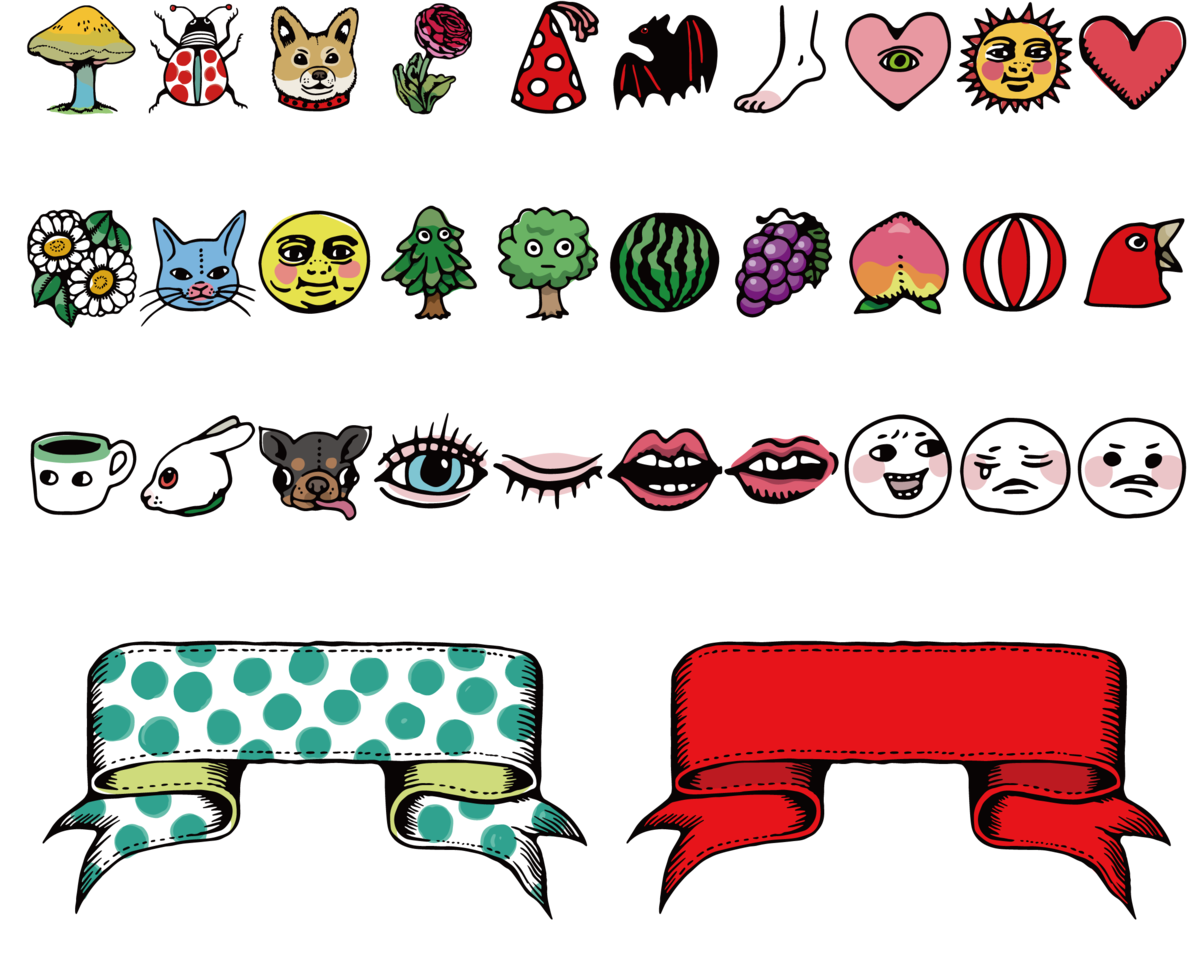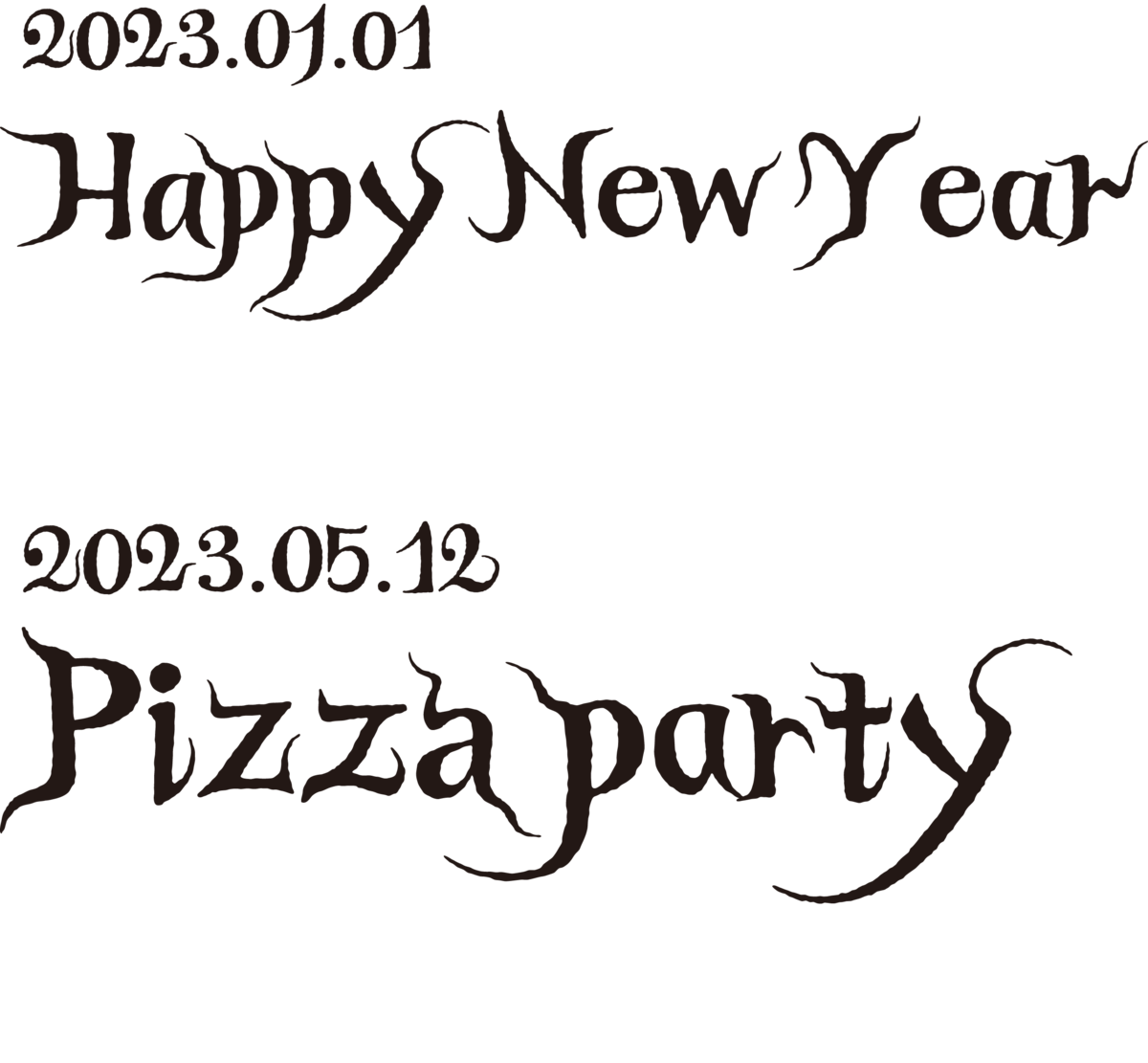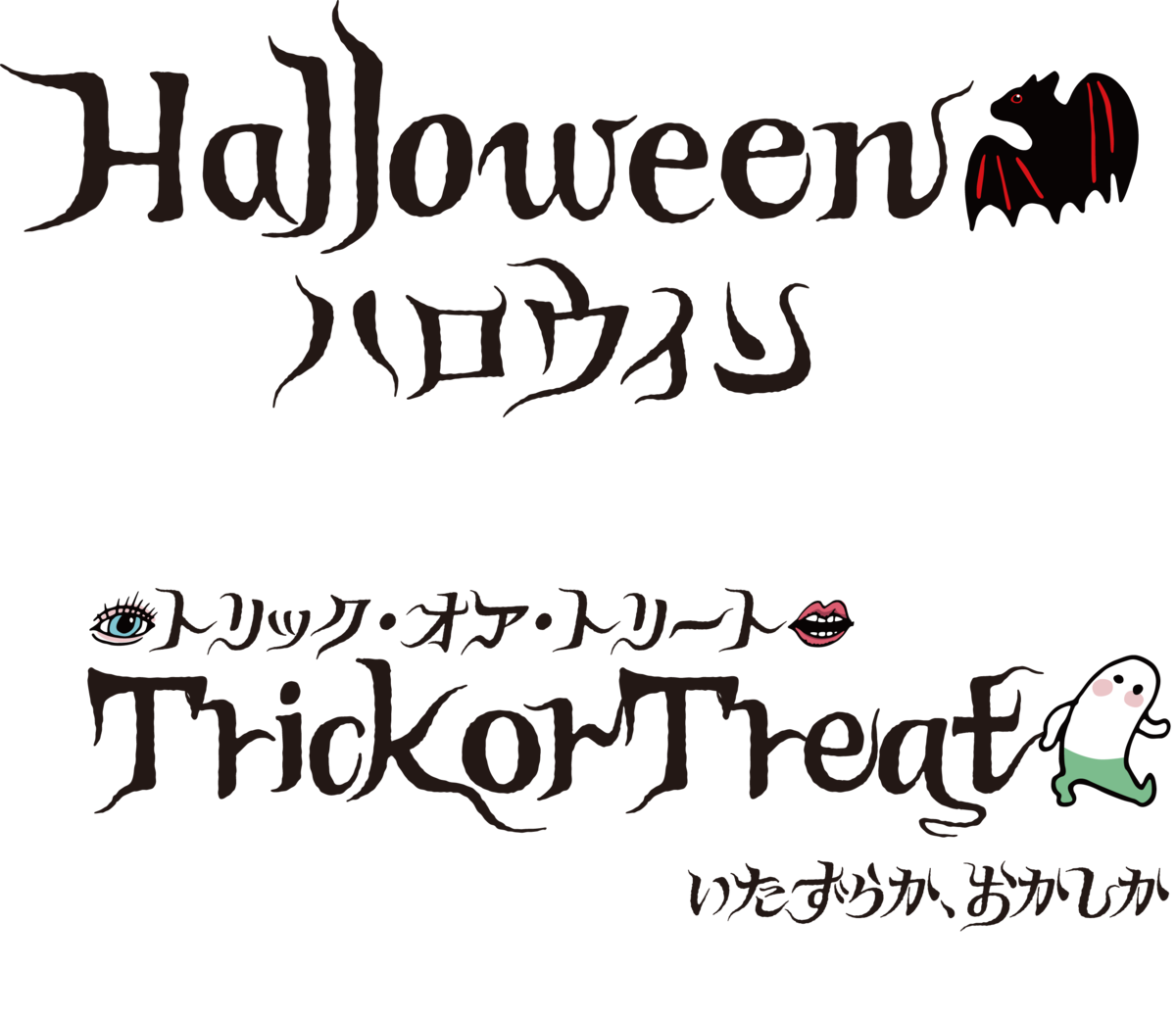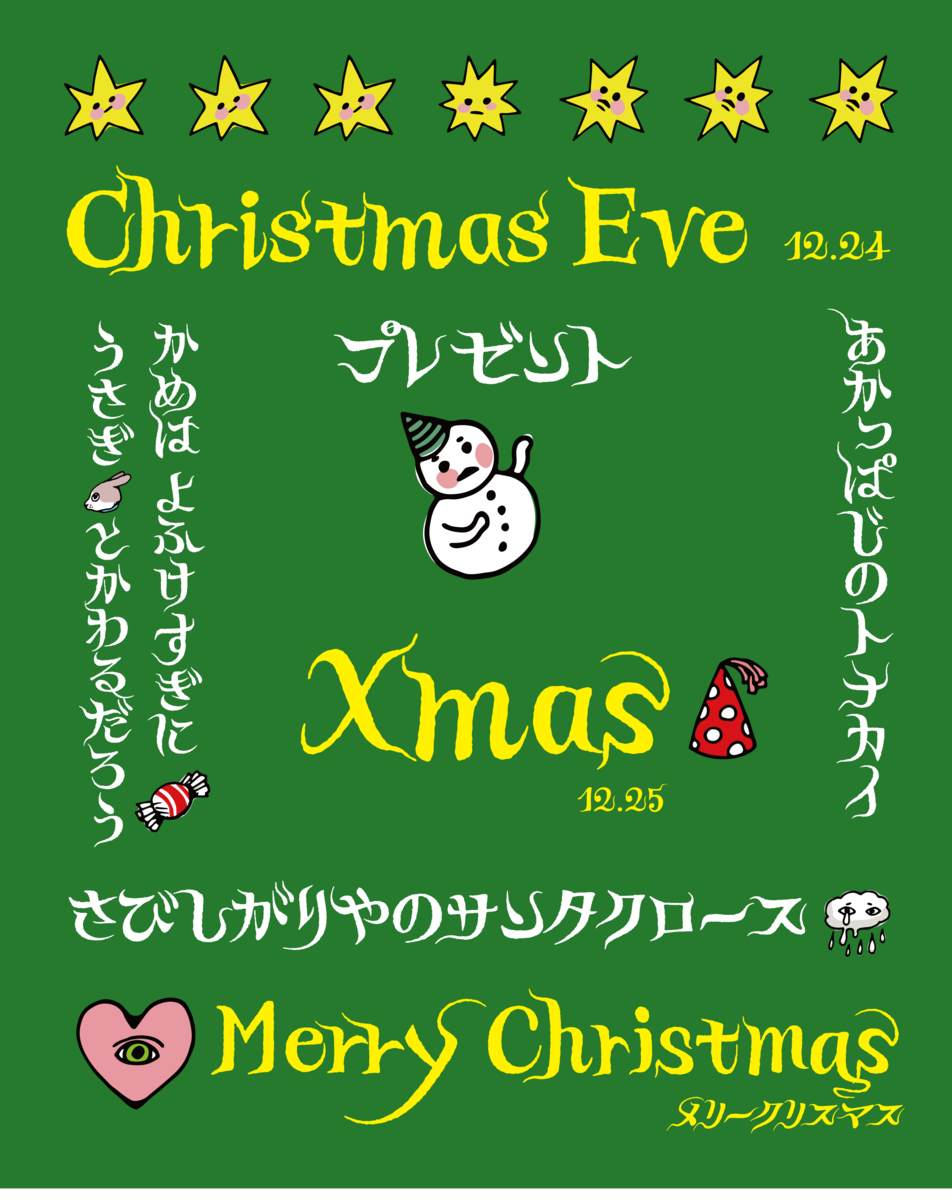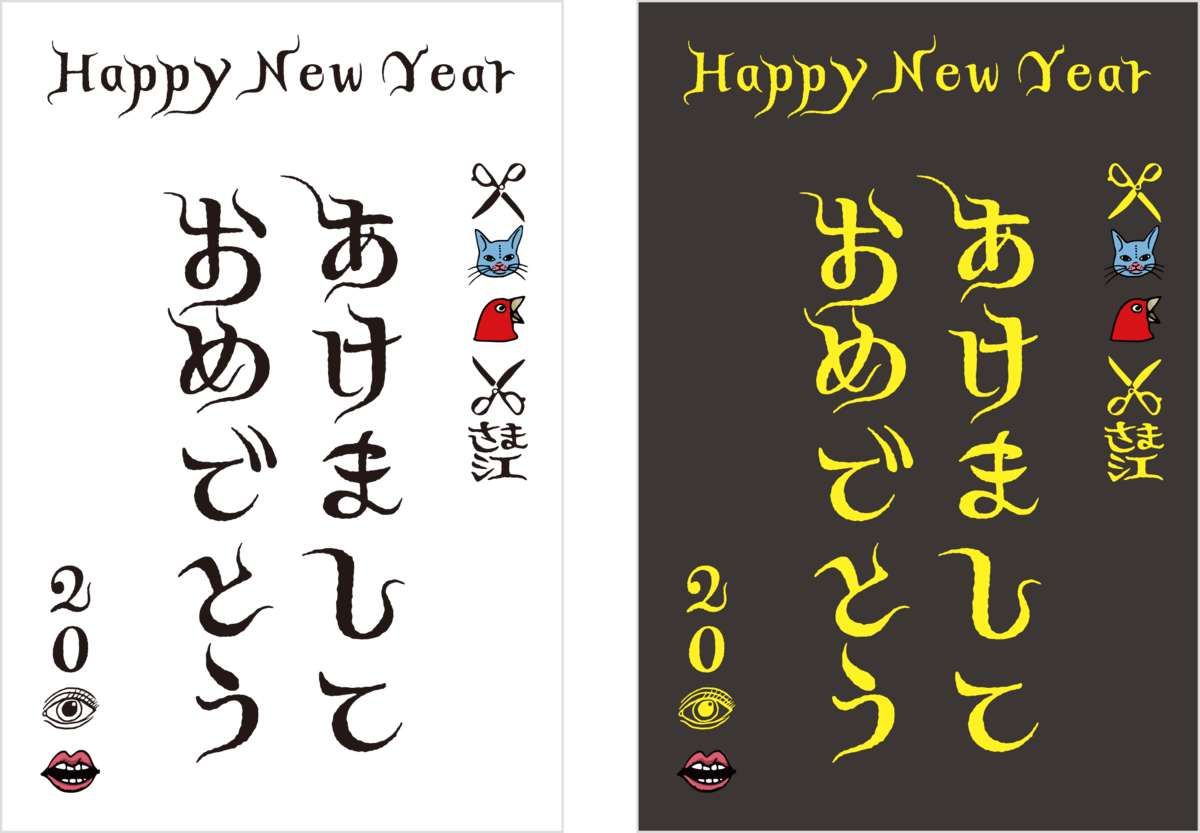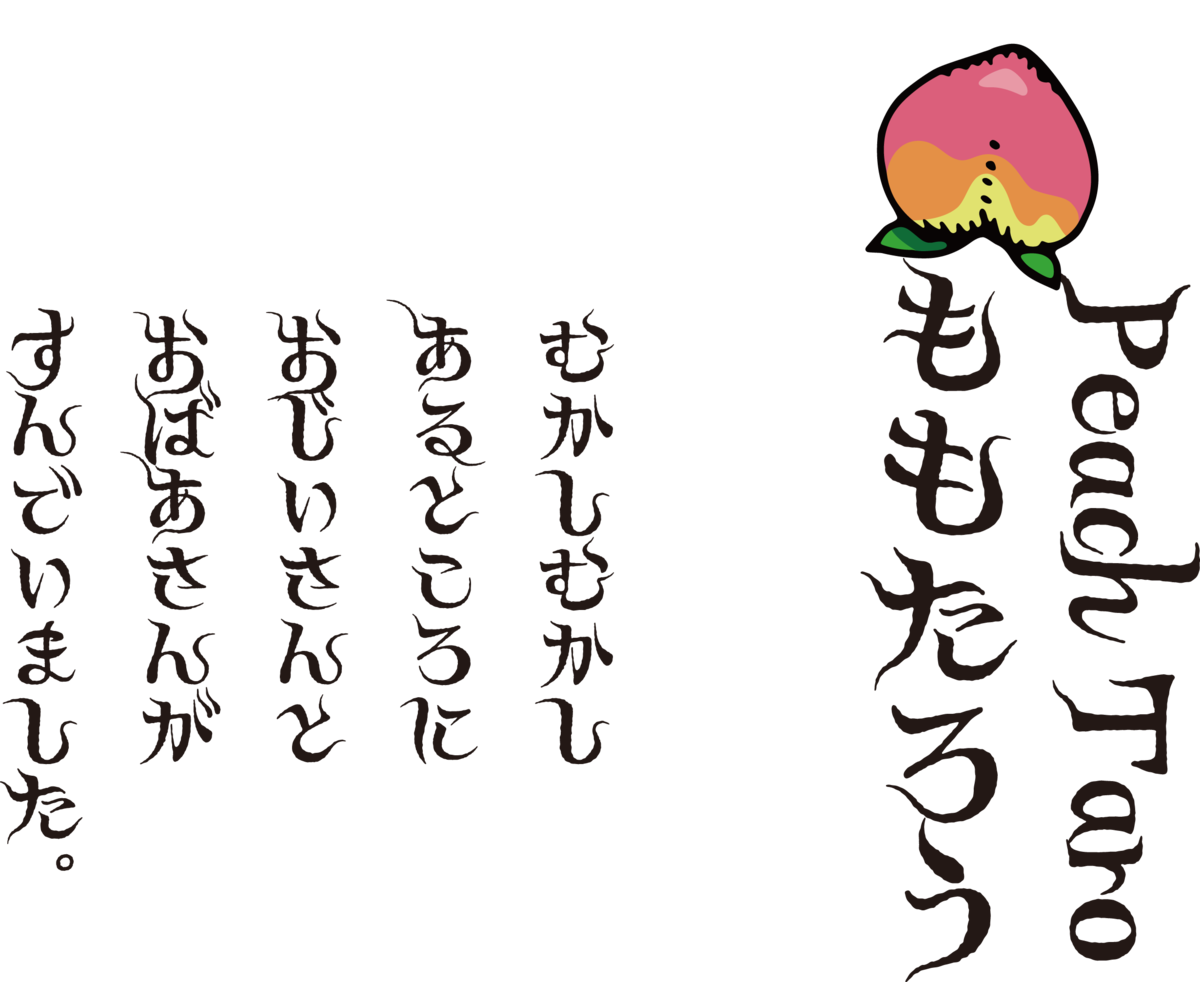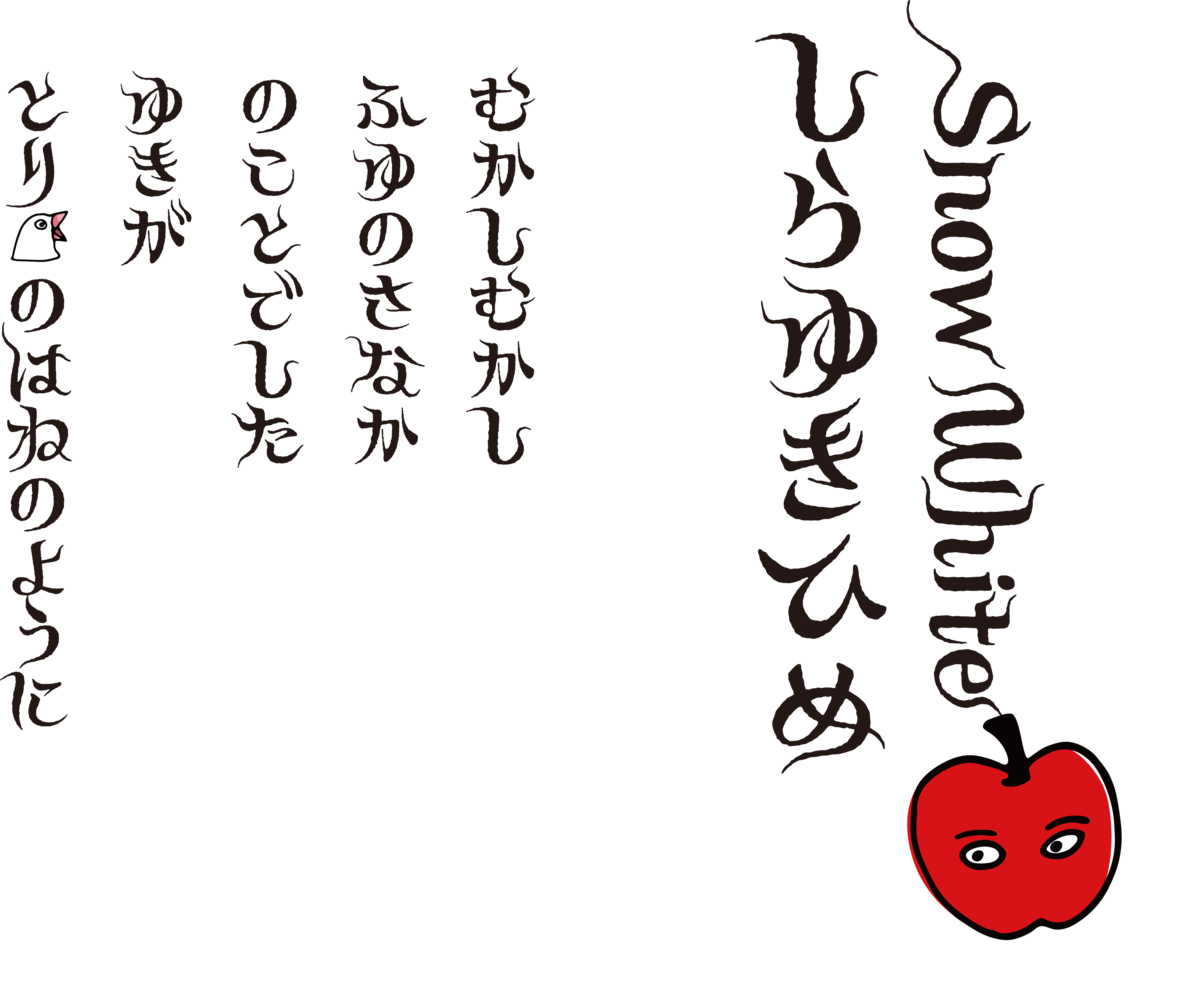
ヒグチユウコ氏の世界観を満喫できるアドビのオリジナルフォント「ヒグミン」
ピクミンでもなく、
ピグモンなんてものでなく、
ましてやビタミンでもない。
コクミンのみんなへとつたえるべく
なまえはヒグミンです。
ヒグミンは、画家でありイラストレーターや絵本作家としても活躍するヒグチユウコ氏とアドビのプリンシパルタイプデザイナー・西塚涼子氏のデザインによる、かなと英数字、絵文字の遊び心にあふれたアドビのオリジナルフォント。
ヒグチユウコ氏の手描き文字と絵をもとに、西塚涼子氏がデザインし、個性的な文字にくわえ、豊富なカラー絵文字が含まれている。
それにしても絵本などを手掛けるヒグチユウコ氏のイラストは適度な毒も味わい深い。
単純に文字も絵文字もかわいらしい。
また、各文字には異体字が数種類用意されており、OpenType機能の「前後関係に依存する字形(calt)」によって、異体字に自動的に切り替わり、手描きの雰囲気が強く醸し出される仕組み。
ヒグチユウコ氏の世界観を感じられる文字は、例えばオリジナル絵本を作成したりするときも楽しめることだろう。
ヒグミン 書体見本